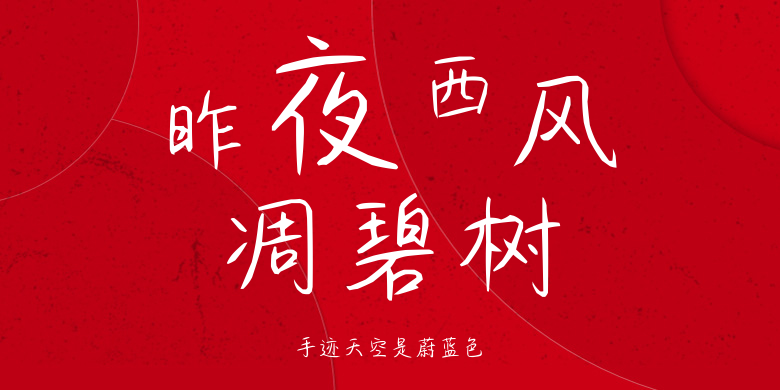
手迹天空是蔚蓝色
手迹天空是蔚蓝色,这款字体结构工整、笔画清晰,兼顾美观与易读性,适用于标题、正文、海报、包装、LOGO 等多种场景。字形优雅稳定,风格百搭耐看,适配日常排版与创意设计,让文字呈现更舒适、更具质感。手迹天空是蔚蓝色一笔一画,皆是细节,以均衡的比例、流畅的线条打造舒适视觉体验,字形端正大气,风格简约现代。无论是商业设计、品牌宣传还是日常排版,都能轻松驾驭,让文字更有格调与力量。手迹天空是蔚蓝色字体下载。